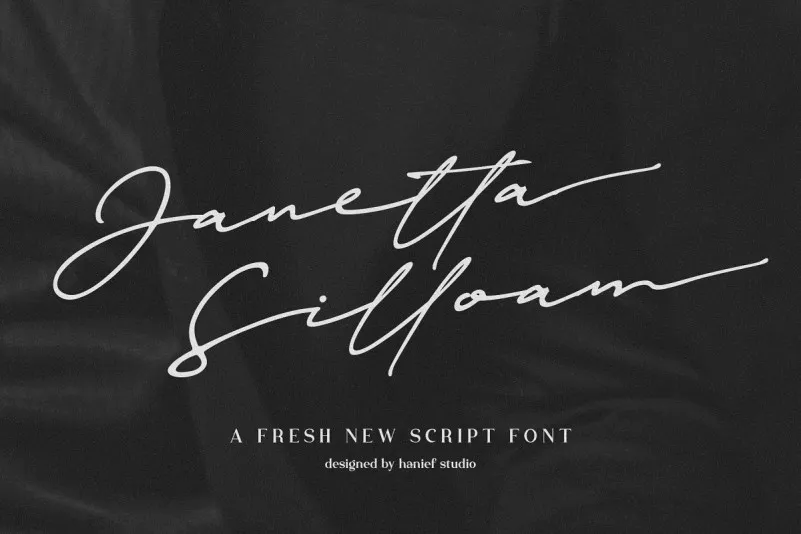
Aqui está uma breve descrição para a página de download da fonte “Janetta Silloam Signature Font”: Janetta Silloam é uma elegante e fresca fonte de script, perfeita para aqueles projetos que buscam um ar delicado e apaixonado. Esta tipografia moderna, com um toque mágico de pressão, é ideal tanto para logotipos quanto para editoriais ou aplicativos gráficos. Seus traços fluidos se adequam perfeitamente a diversos formatos de design, desde cartões de visita e panfletos até rótulos e embalagens. A fonte oferece uma gama completa de letras manuscritas, tanto maiúsculas quanto minúsculas, números e um amplo leque de pontuações e ligações. O diferencial desta fonte é a inclusão de “swashes” nas letras minúsculas, que as dão um apelo mais autêntico e realista. Janetta Silloam é uma excelente escolha para aqueles projetos que desejam adicionar um toque único e delicado ao seu design. Com sua facilidade na leitura e o estilo manuscrito perfeito de Janetta Silloam, você pode capturar a essência da paixão em seus trabalhos.